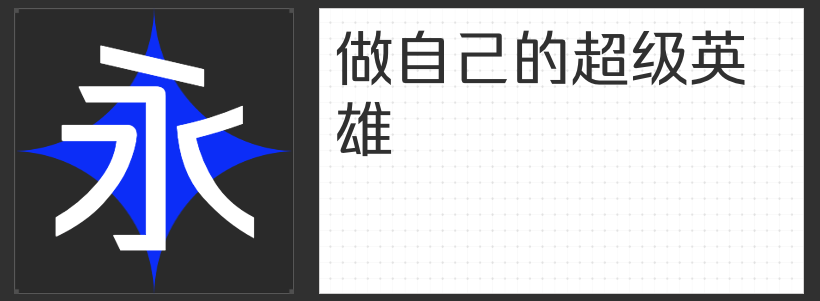
四款电商设计「吸睛利器」字体推荐:从标题到正文的视觉升级指南
在电商设计的视觉竞争中,字体不仅是信息传递的载体,更是塑造品牌调性、提升用户停留时长的关键元素。一款适配的字体能瞬间强化商品吸引力,从标题的冲击力到正文的易读性,均需精准拿捏。以下四款专业字体以独特的设计语言,为电商设计提供多元化解决方案:
一、励字志向黑简 常规
励字志向黑简 常规以黑体为骨架,融入圆体基因,通过笔画拐角的外圆角处理,在硬朗结构中注入柔和气质。这种设计既保留了黑体的正式感,又避免了过于生硬的视觉体验,尤其适合需要传递专业性与亲和力并存的场景。其字面充实、结构稳定的特点,在屏幕显示中能清晰呈现细节,无论是商品分类标签还是促销副标题,均能保持视觉舒适度。
二、励字勇敢黑简 大黑
作为无衬线字体的极致演绎,励字勇敢黑简 大黑以粗壮笔划与均匀横竖线条构建醒目视觉。撇捺笔画采用钝角收尾,避免尖锐感,既提升阅读流畅性,又强化了字体的现代感。其大黑字重设计,使其成为标题、导语或品牌标志的理想选择,尤其在需要突出核心卖点或营造紧迫感的促销场景中,能瞬间抓住用户注意力。
三、励字超级勇士简 准粗
以黑体为基准,励字超级勇士简 准粗通过简化笔画与圆弧转折处理,打造出张弛有度的结构。其准粗字重既不过分厚重,又保持了足够的存在感,布白空间通透的设计让长文本阅读更轻松。这款字体适合商品详情页的正文描述,既能保持整体设计的一致性,又能通过适度留白提升信息层次感。
四、励字综艺简繁
励字综艺简繁以超粗笔画填满空间,拐弯处采用圆润方正的处理,在横平竖直中融入活泼基因。其艺术性极强的设计语言,既能驾驭潮流品牌的个性表达,也可为传统商品注入时尚感。无论是作为主视觉的点缀元素,还是独立成为设计焦点,均能通过强烈的视觉冲击力强化品牌记忆点。
这四款字体从稳重到灵动、从力量到艺术,覆盖电商设计的多元需求,助力设计师在信息传递与视觉美感间找到完美平衡。